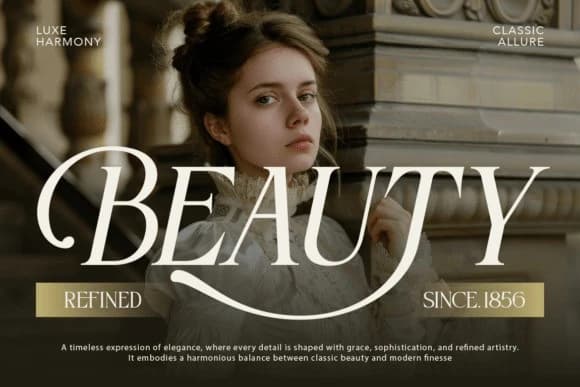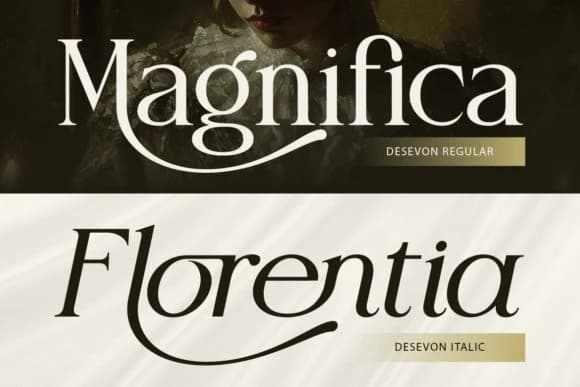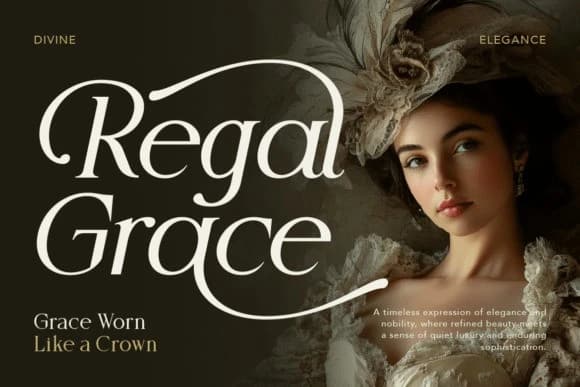
Desevon Font
Desevon Font, tasarımlarınıza zamansız güzellik ve modern zarafet getirmek için özenle tasarlanmış zarif ve rafine bir serif yazı tipidir. Zarif eğrileriyle, yüksek kontrastlı hatlarıyla ve lüks ligatürlerle Desevon, klasik tipografinin özünü yakalar ve buna çağdaş bir dokunuş katar.
Desevon Font, tasarımlarınıza zamansız güzellik ve modern zarafeti kazandırmak için tasarlanmış zarif ve sofistike bir serif yazı tipidir. Zarif eğrileri, yüksek kontrastlı hatları ve lüks ligatürleriyle Desevon, klasik tipografinin özünü yakalarken çağdaş bir dokunuş da katıyor.
Desevon